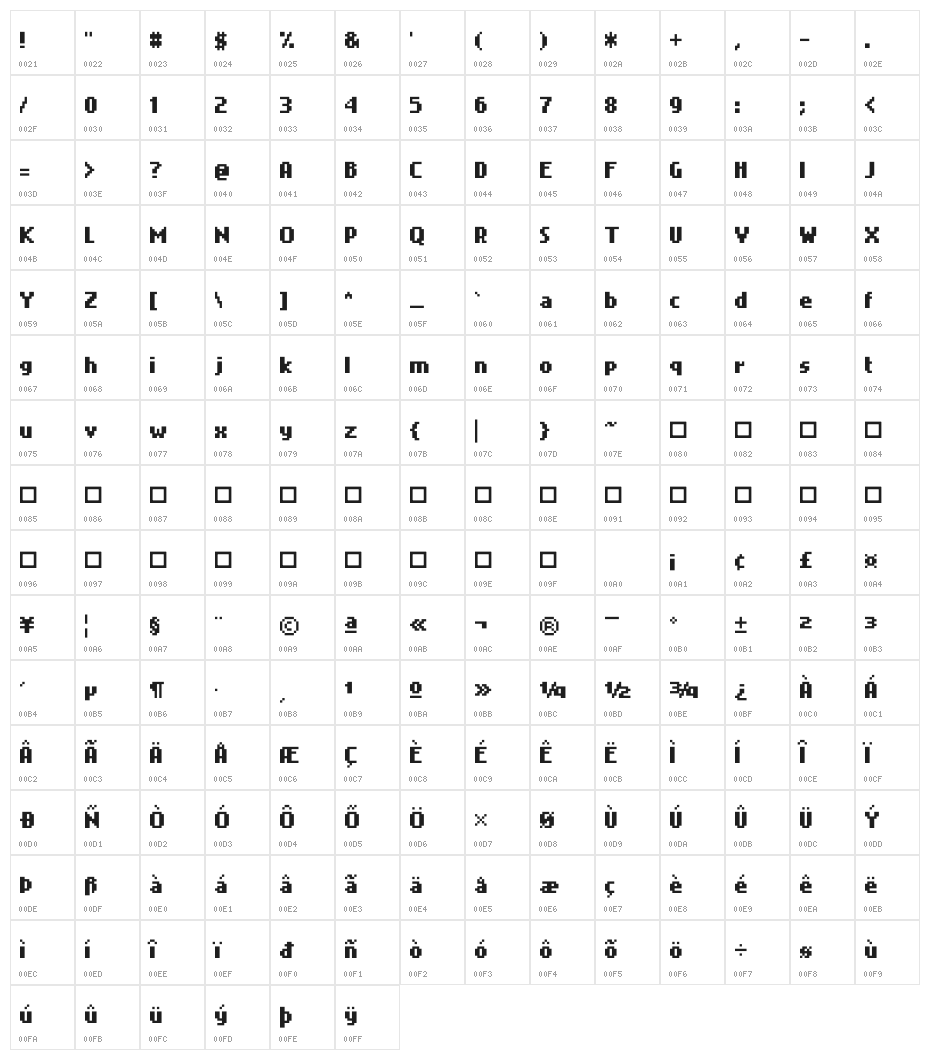
Bit Cell Font
memesbruh03 - Aaron D. Chand
| Gesamtstil | Retro, Digital |
| Vorgeschlagene Projekte | Perfect for retro video game designs, tech-themed posters, digital art, and any project needing a nostalgic digital touch. |